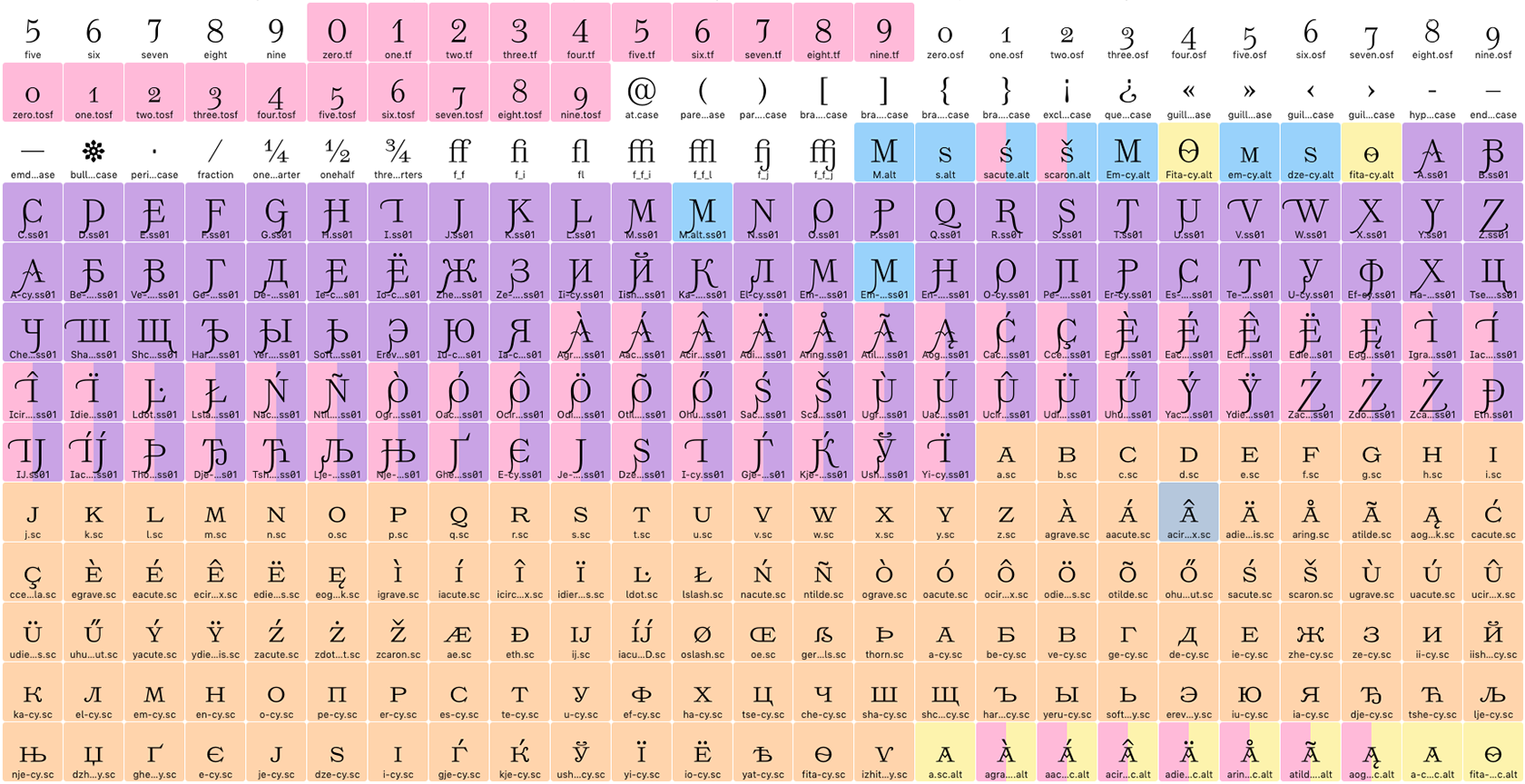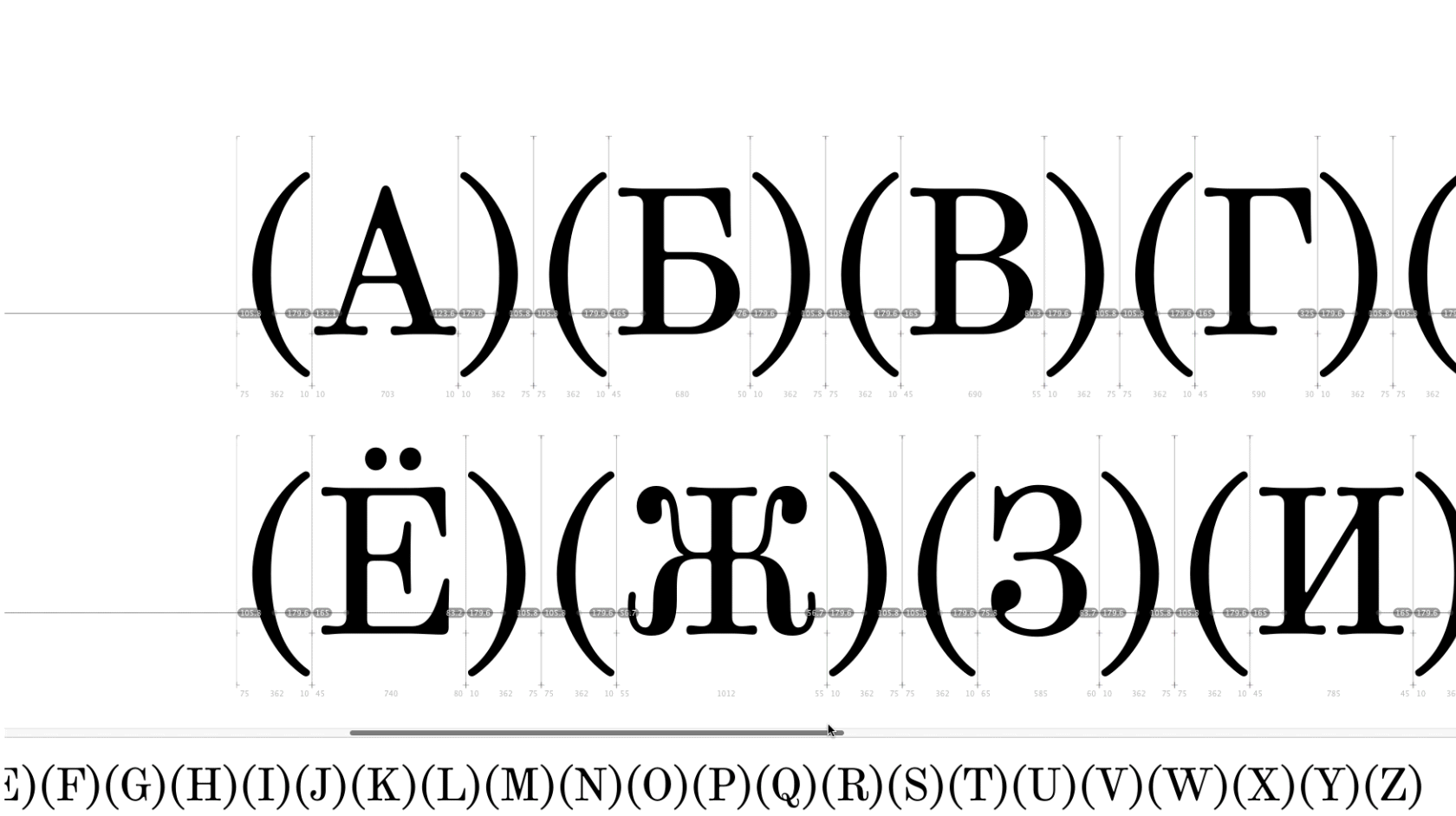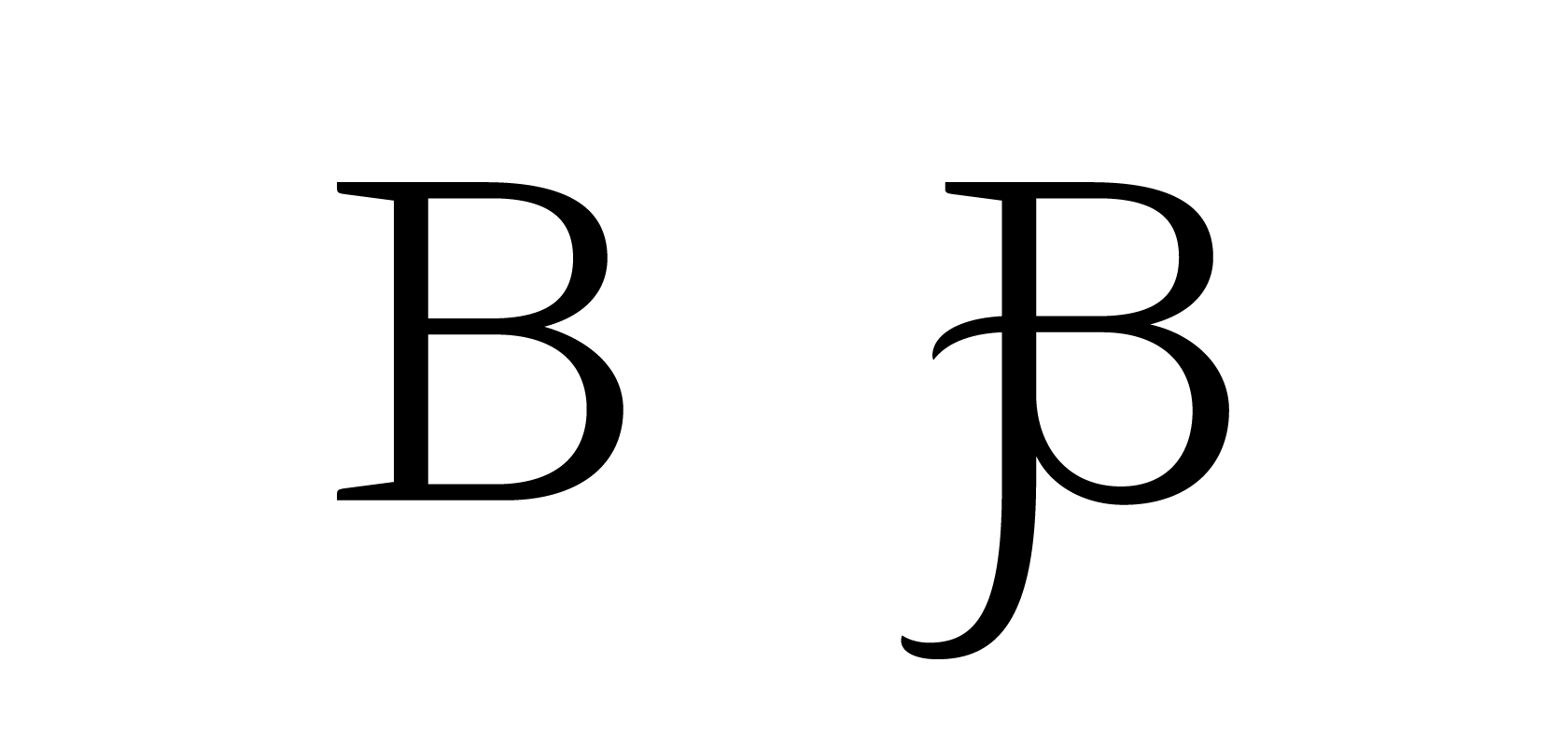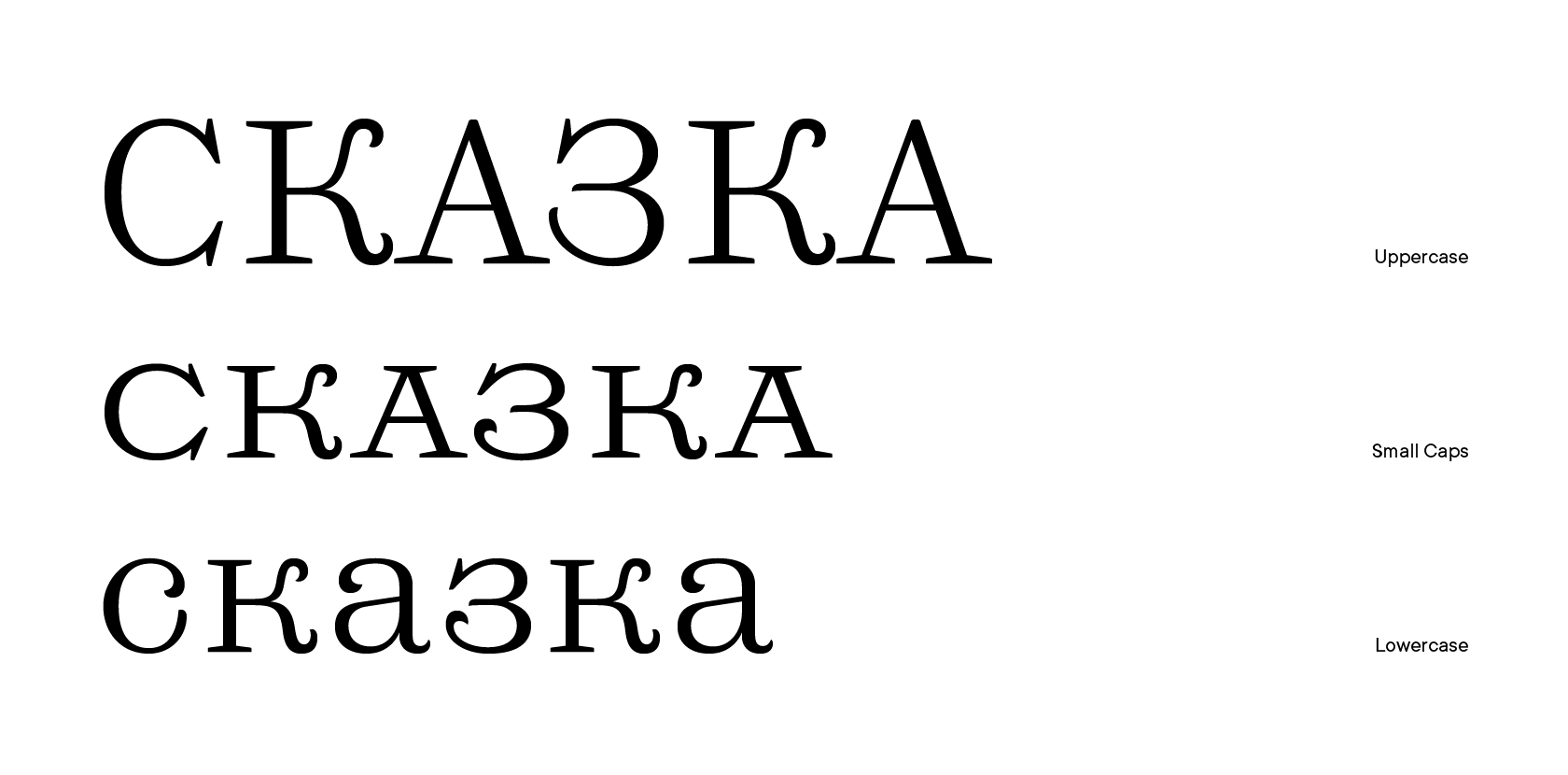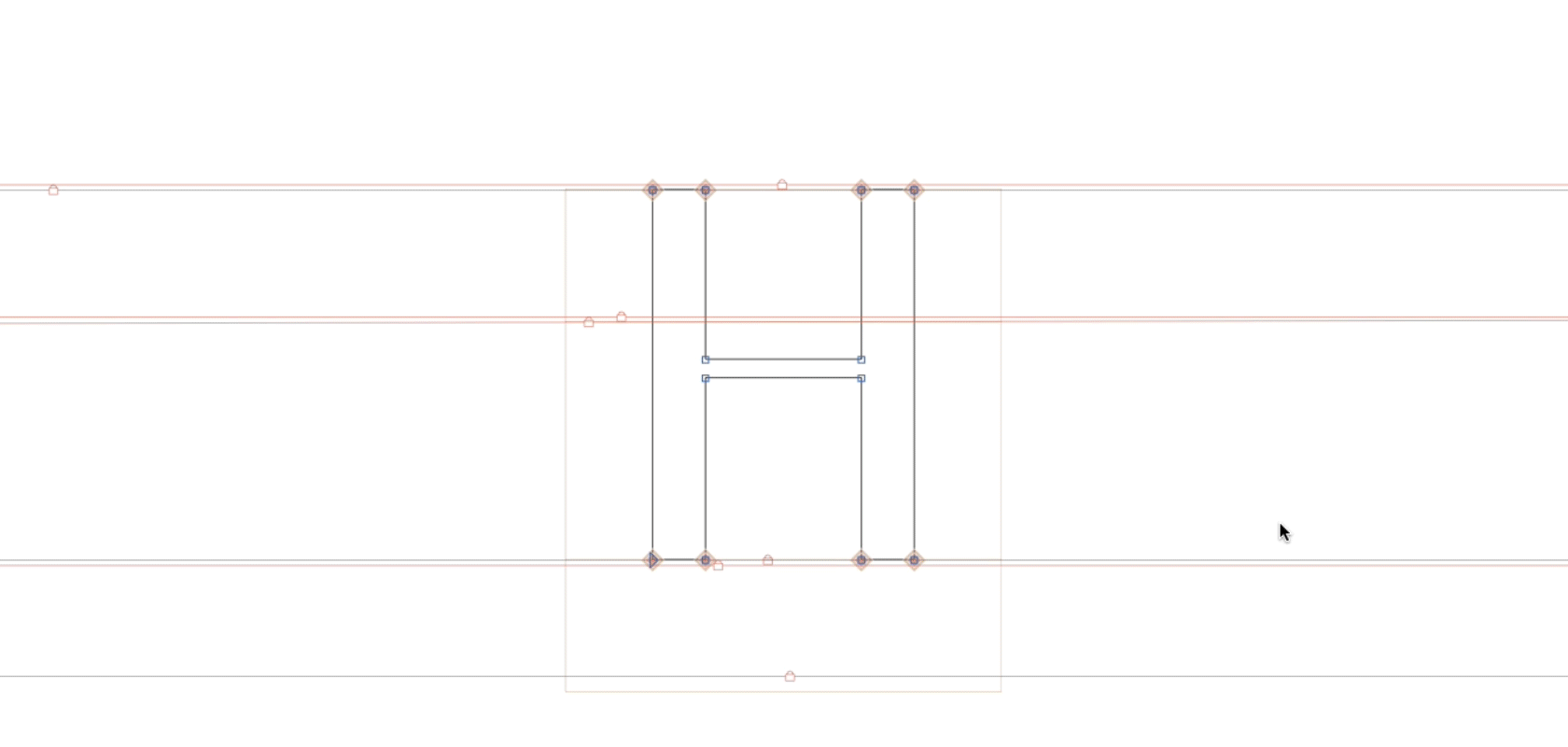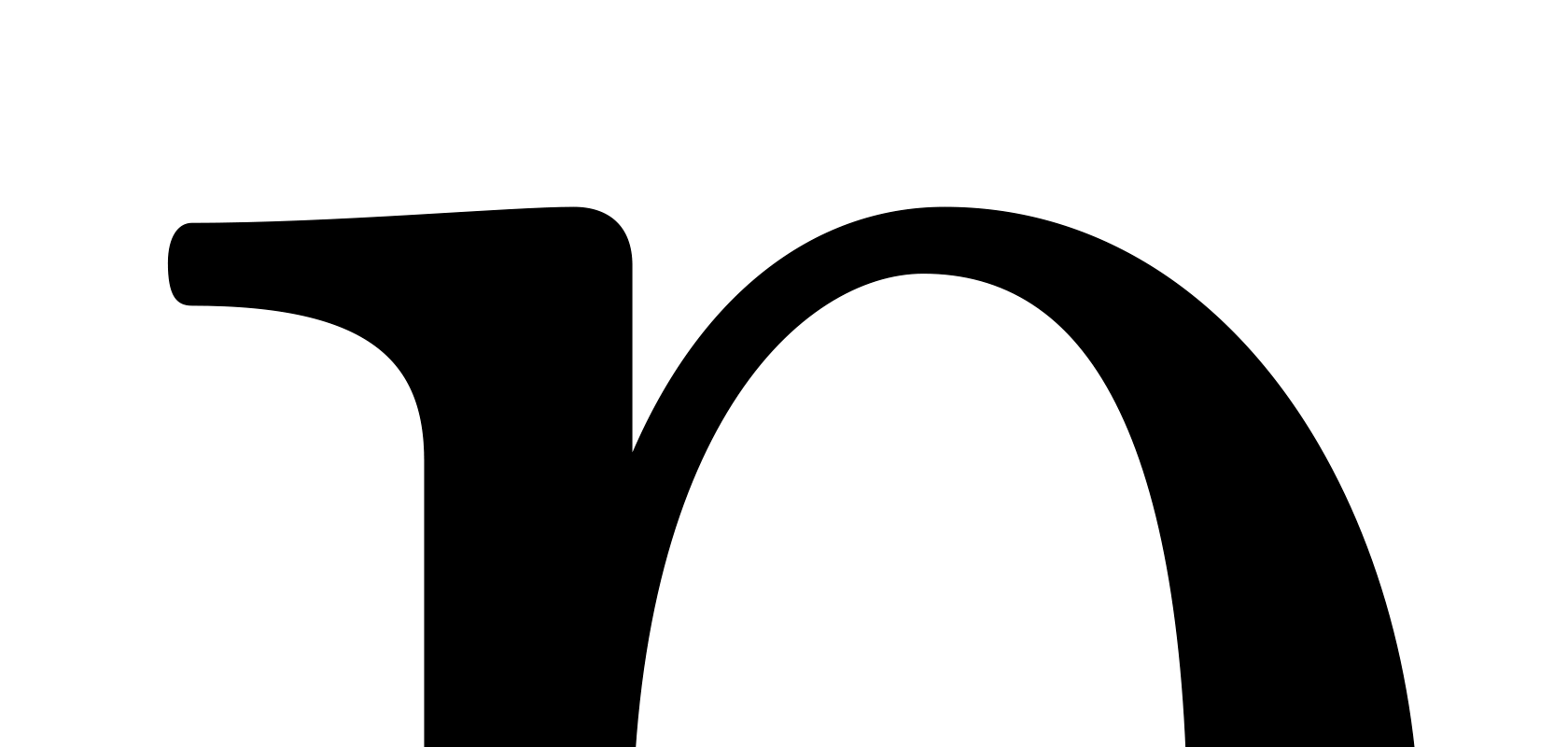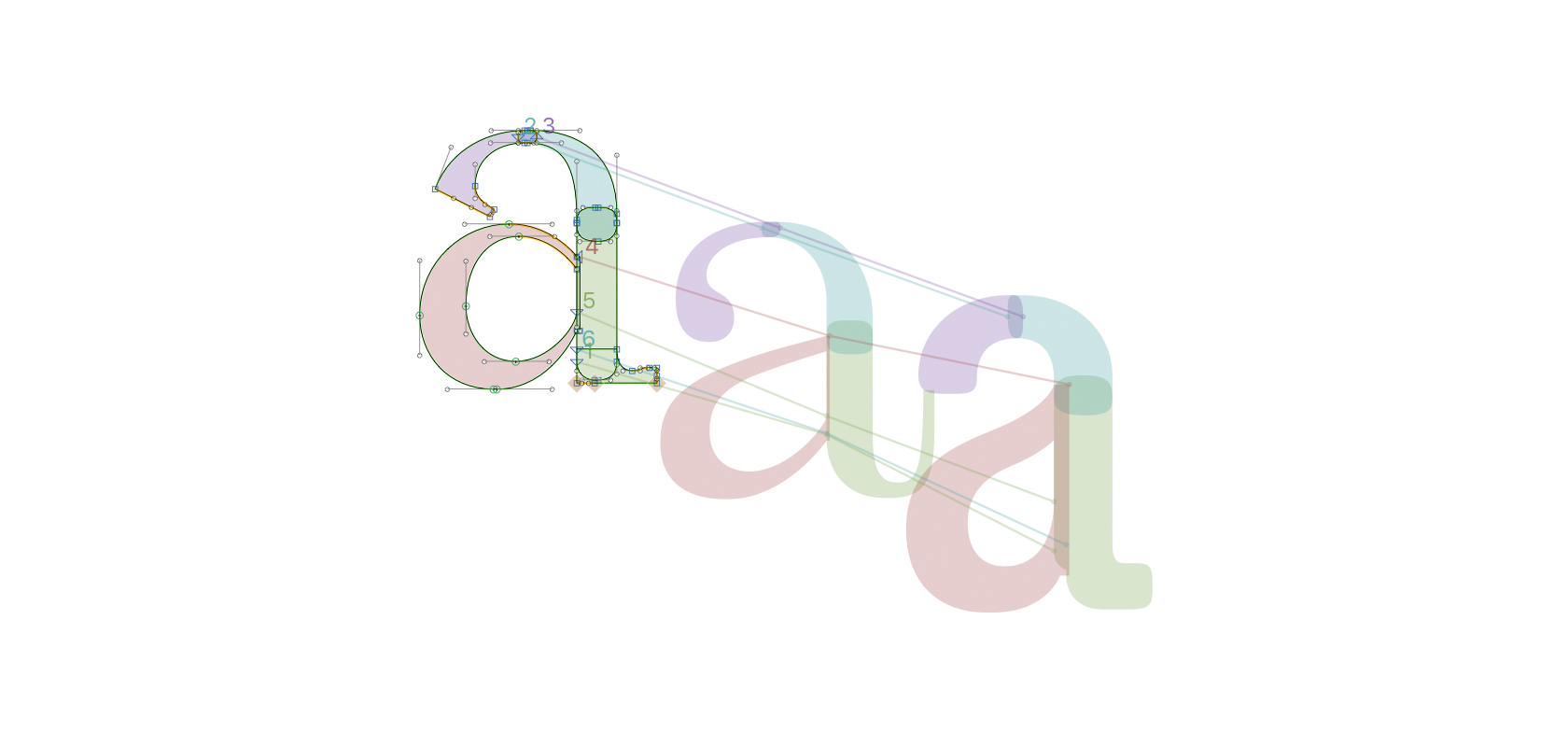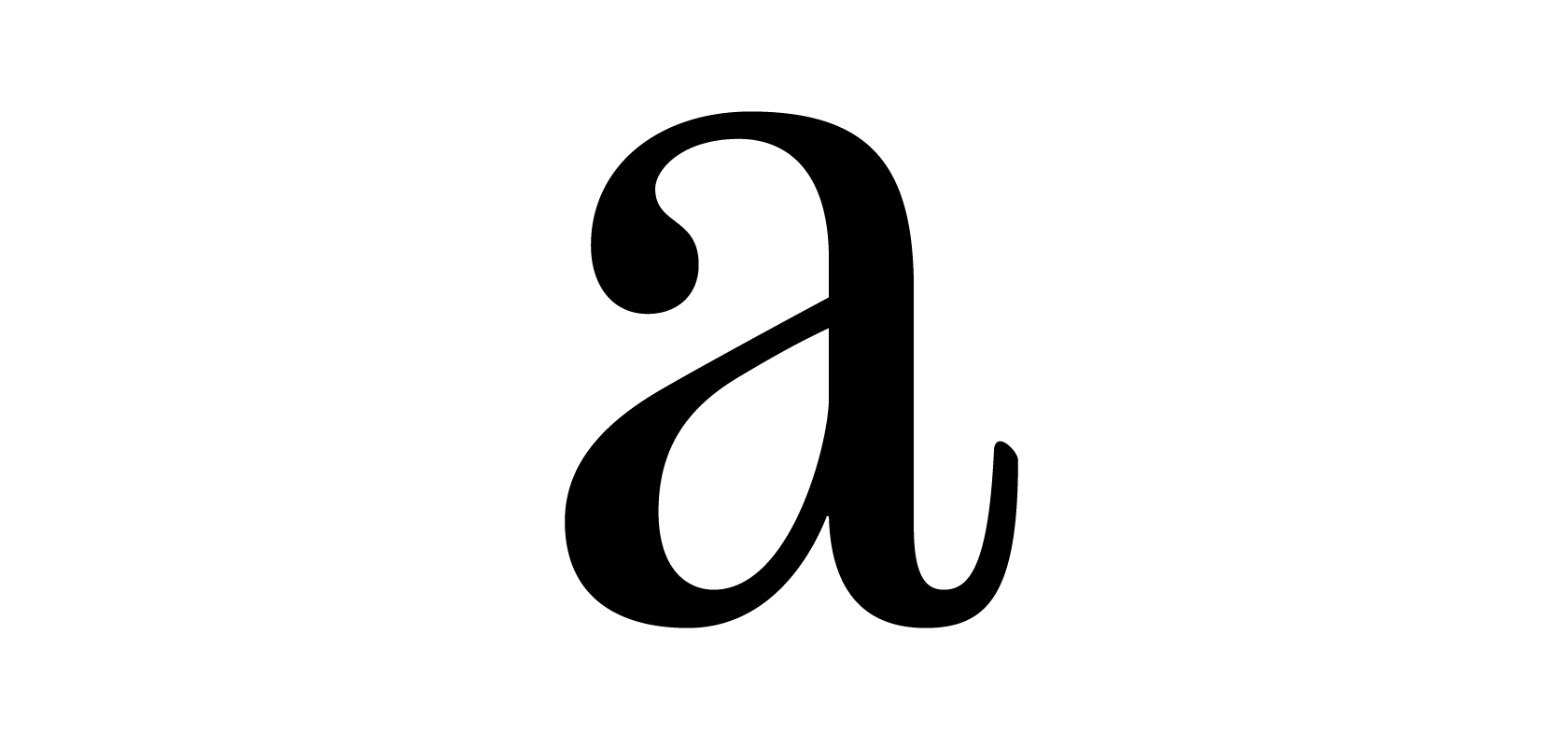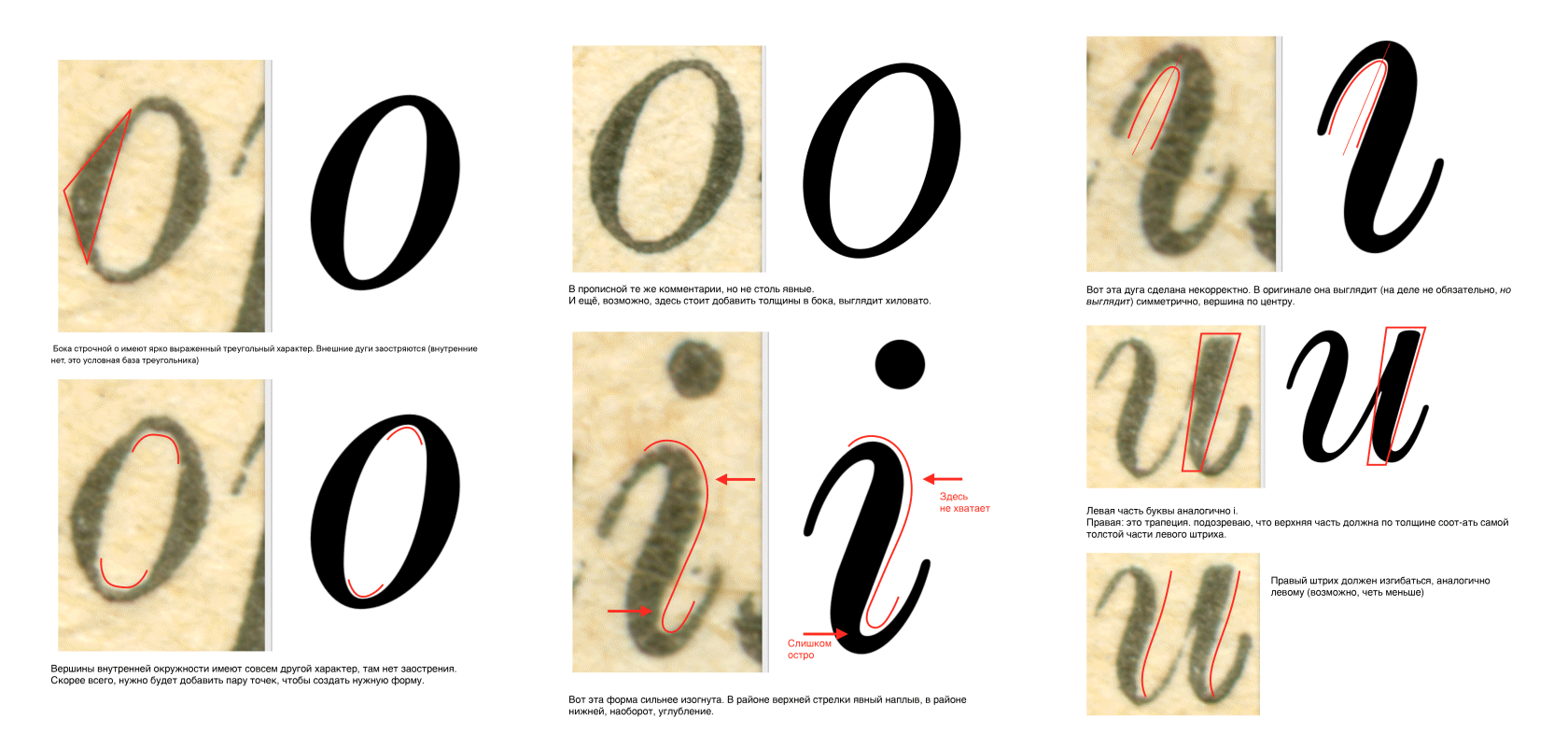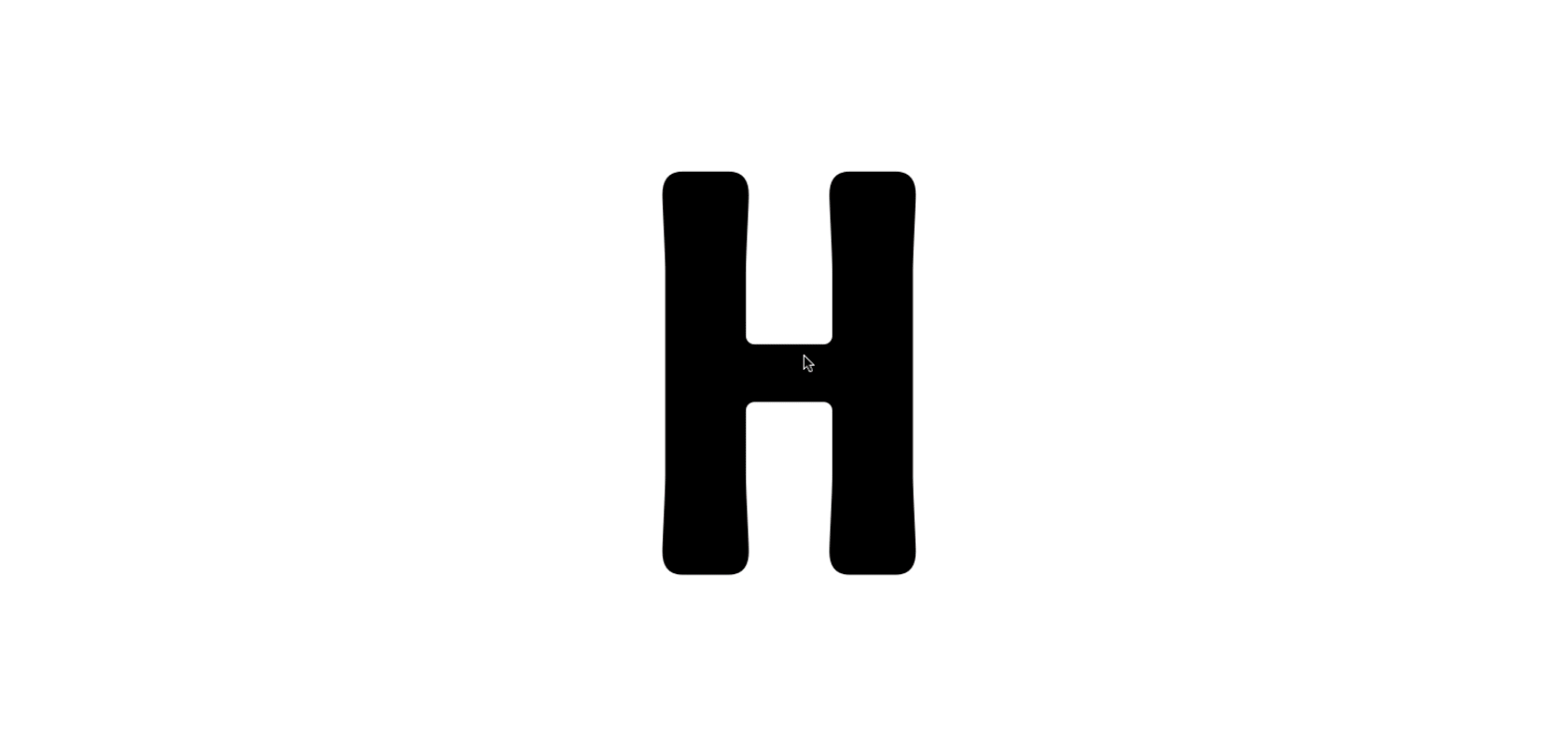
История TT Marxiana
Рады представить вам историю создания проекта шрифтовой гарнитуры TT Marxiana.
TT Marxiana является проектом по реконструкции набора дореволюционных шрифтов, которые использовались в вёрстке журнала «Нива», издававшемся Санкт-Петербургским издательством А.Ф. Маркса. В нашем проекте мы решили остановиться на конкретном наборе шрифтов, которые использовались в изготовлении и печати журнала «Нива» 1887 года выпуска, а именно на антикве, италике, гротеске и эльзевире.
В рамках проекта TT Marxiana мы стремились придерживаться строгой историчности и сохранить максимальную близость к бумажному первоисточнику. Мы старались избежать какого-либо «осовременивания» шрифтов, если, конечно, не считать за таковое работу с кернингом, внедрение OT фич и создание ручного хинтинга. В итоге дизайнер получает с гарнитурой TT Marxiana полноценный и функциональный набор разных шрифтов, позволяющий современными методами и с помощью современных программ создать, например, журнал с дизайном, который был характерен для конца 19 века.
1. Начало проекта
Летом 2018 года мы задумались о том, что было бы неплохо сделать проект ревайвала (или реконструкции) нескольких исторических шрифтов, которые достаточно активно использовались 100 и более лет назад. Мы подумали о том, что это было бы неплохим вкладом в частично потерянную дореволюционную культуру, а также было бы отличной возможностью познакомить современных дизайнеров с действительно историческим шрифтовым проектом.
В этот период в России уже существовало несколько крупных и продвинутых типографий, а сам архетип кириллицы был сформирован до привычного нам образа. Кроме того, несмотря на потерю самих шрифтовых наборов, сохранилось достаточно много печатных образцов книг того времени, а значит, среди них можно было бы найти самые интересные шрифты.
При поиске идей мы рассматривали период конца XIX – начала XX веков и фокусировались именно на русских дореволюционных типографиях.
2. Библиотека и источники
Первоначально, планируя походы в библиотеку, мы думали о том, что будем изучать только дорогие подарочные издания, и искать в них шрифтовые жемчужины. В библиотеках и электронных архивах действительно попадались очень интересные образцы шрифтов.
Первый поход в библиотеку
В процессе исследования мы обнаружили, что в книгах, отпечатанных в разных типографиях, можно было наткнуться на одни и те же шрифты, или близкие вариации на их тему.
Во время одного из посещений библиотеки мы нашли книгу от издательства А.Ф. Маркса, которая и стала точкой отсчёта нашего проекта. В этом трёхтомнике мы обнаружили комплект шрифтов, которые хорошо подходили для реализации нашей идеи.
Трёхтомник «История русской словесности» издательства А.Ф.Маркса
После этой находки мы окончательно остановились на идее создания комплекта шрифтов, которые бы не диссонировали между собой, а, наоборот, дополняли друг друга общим восприятием. При этом шрифты должны были быть абсолютно разными по стилистике и иметь индивидуальные особенности, такие как «стиль», «характер», «историчность», «эмоциональность», «дух времени» и др.
3. Отрисовка трёх начертаний или первая версия проекта
Первоначально мы планировали делать все работы в шрифтовом редакторе, но так как он не позволял адекватно работать с растровыми референсами, всю трассировку с бумажных источников мы сделали в графическом редакторе. Такой подход в дальнейшем осложнил нам работу, потому что кривые безье в графических редакторах не дают той свободы действия и бережного отношения к контуру, которые есть у специализированных шрифтовых редакторов. Однако для первого этапа этого было вполне достаточно. Первые цифровые наброски заставили подумать как об основных характеристиках шрифтов (пропорции, контраст, форма засечек), так и над общей концепцией проекта.
Первая попытка оцифровки шрифта
4. Работа над вариативным шрифтом или тупиковый путь
После появления первых набросков мы ещё раз вернулись к обсуждению концепции нашего проекта. Мы размышляли над составом шрифтового семейства и над самим понятием ревайвала (реконструкции). Понятие шрифтового ревайвала можно трактовать двояко: с одной стороны, термин означает полную идентичность с оригиналом, а с другой он также даёт возможность на некоторое самостоятельное высказывание на заданную тему.
На тот момент времени мы не до конца понимали, куда именно нам нужно двигаться. Мы могли сделать как самостоятельный шрифт, основанный на старом источнике, и при этом имеющий определенную художественную и функциональную новизну, так и полностью восстановленный исторический шрифт без излишеств и наших «пожелалок».
В результате мы выбрали неправильный путь художественной самостоятельности – увлеклись трендами и новыми программными возможностями, и приняли решение развить наш проект в экспериментальный вариативный шрифт.
Идея была довольно любопытная и мы потратили немало времени на то, чтобы найти наиболее гармоничные переходы одного шрифта в другой через вариативность. Для большей плавности мы подправили формы засечек и некоторые другие детали шрифта, тем самым ещё больше удалившись от первоисточника.